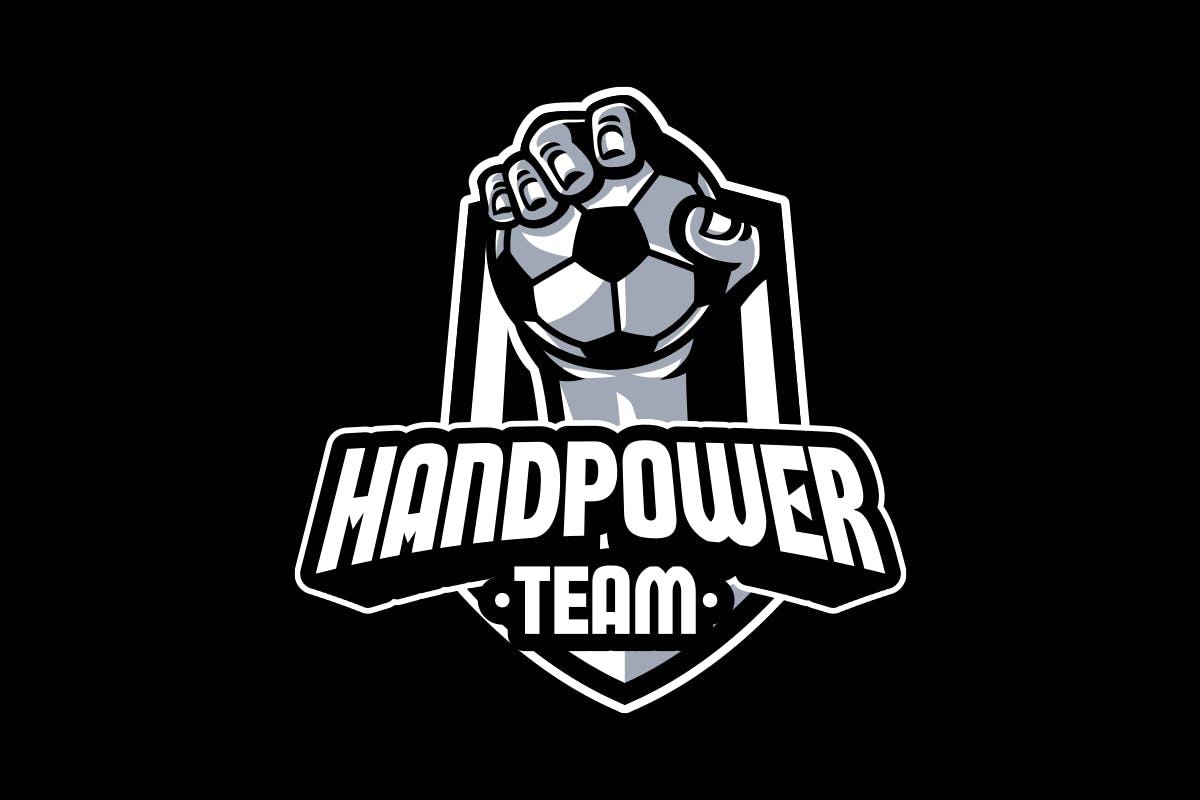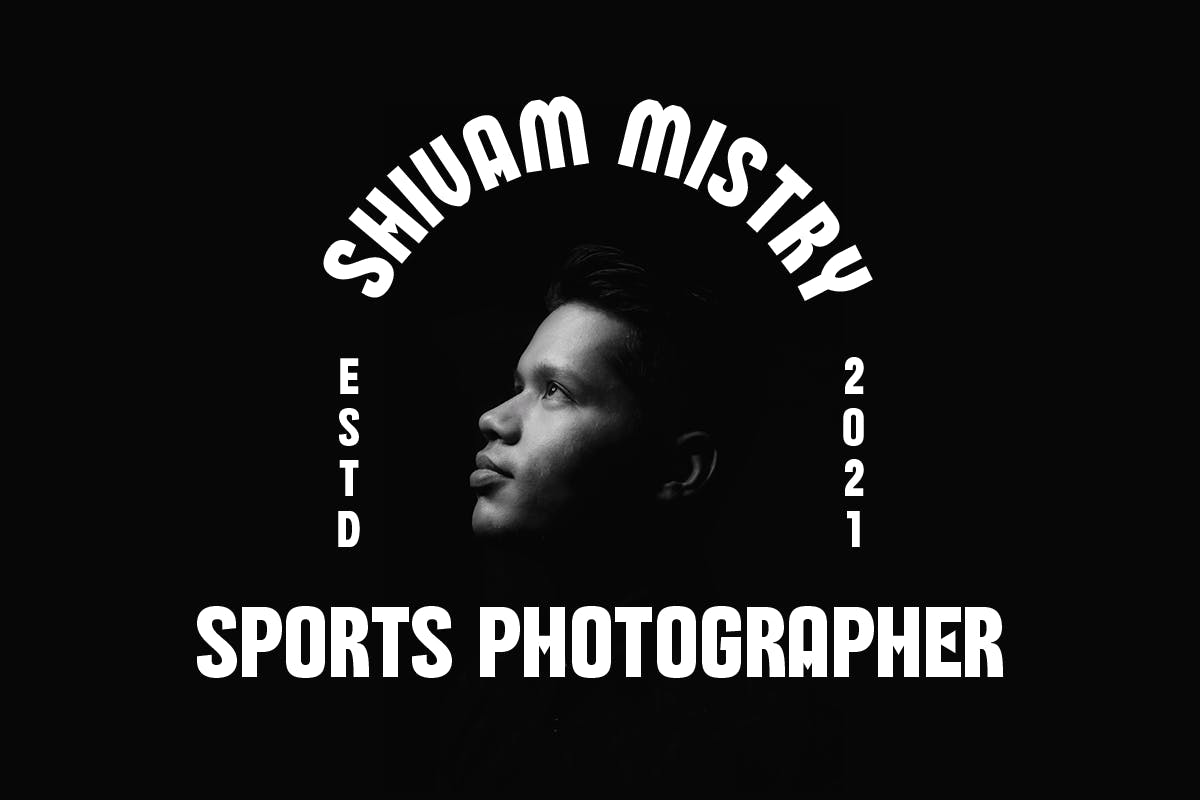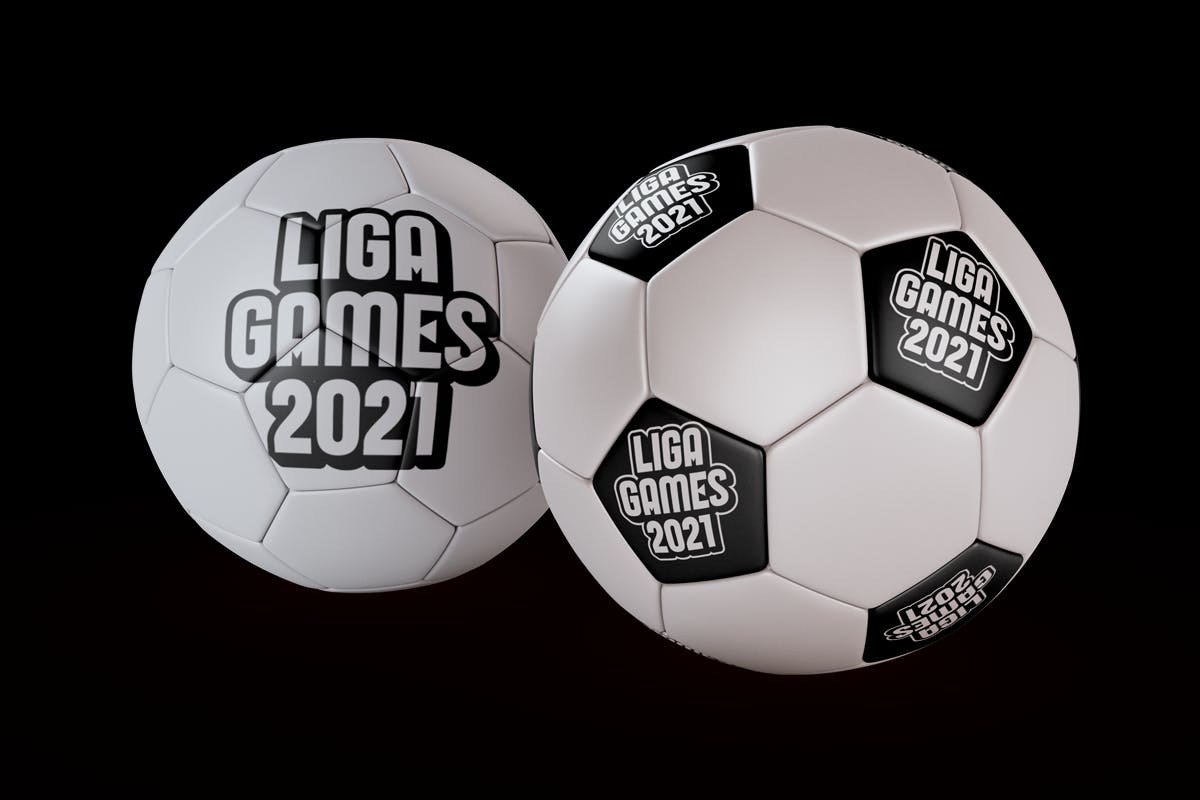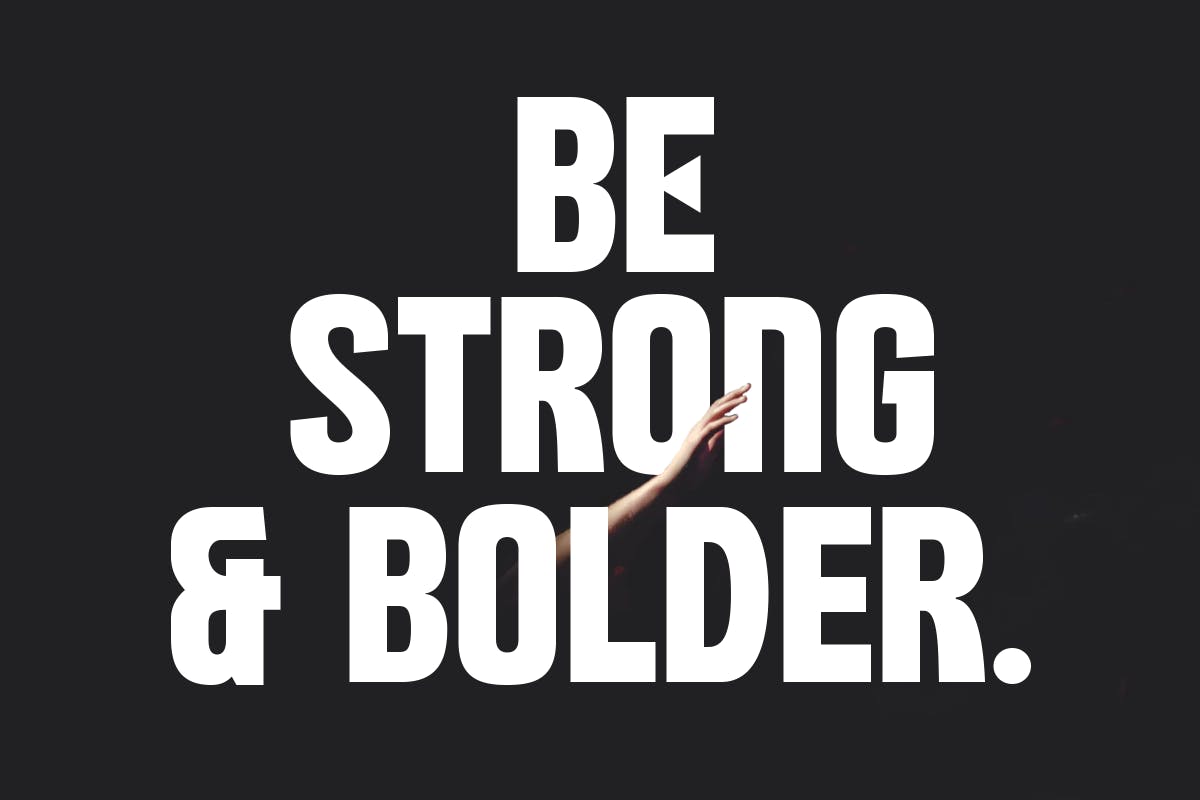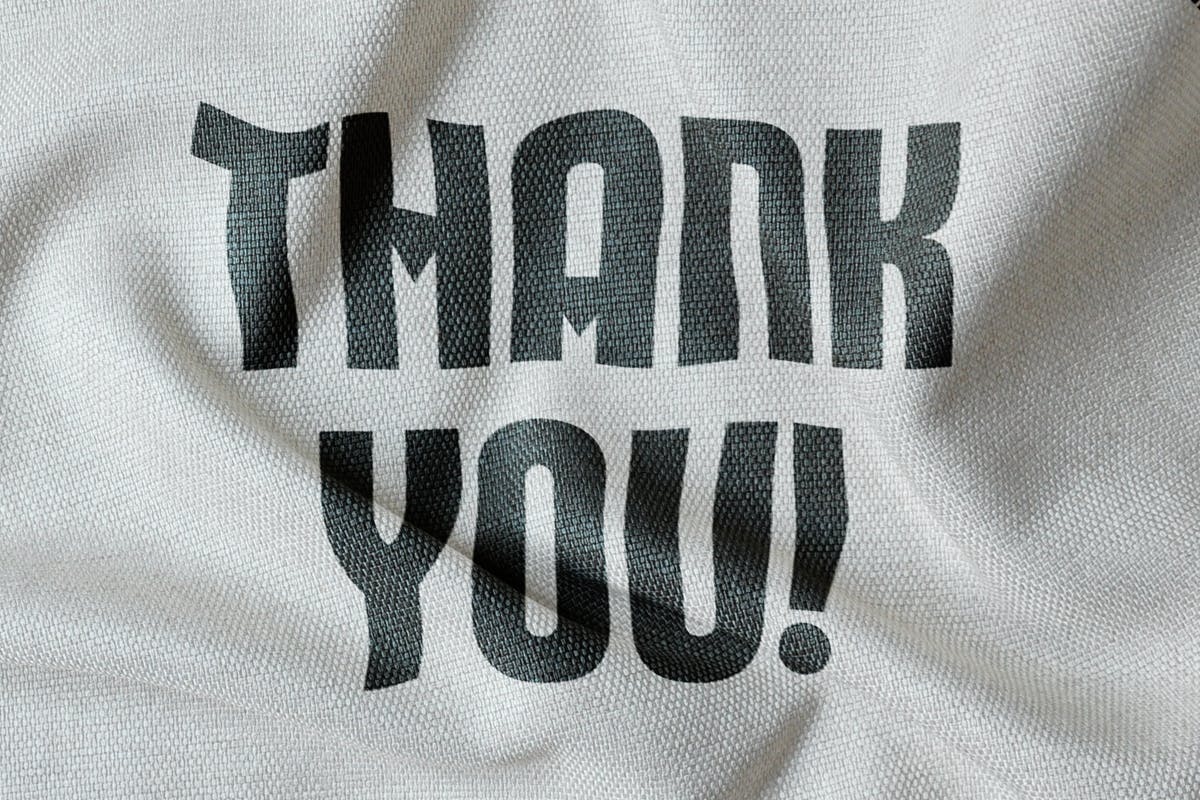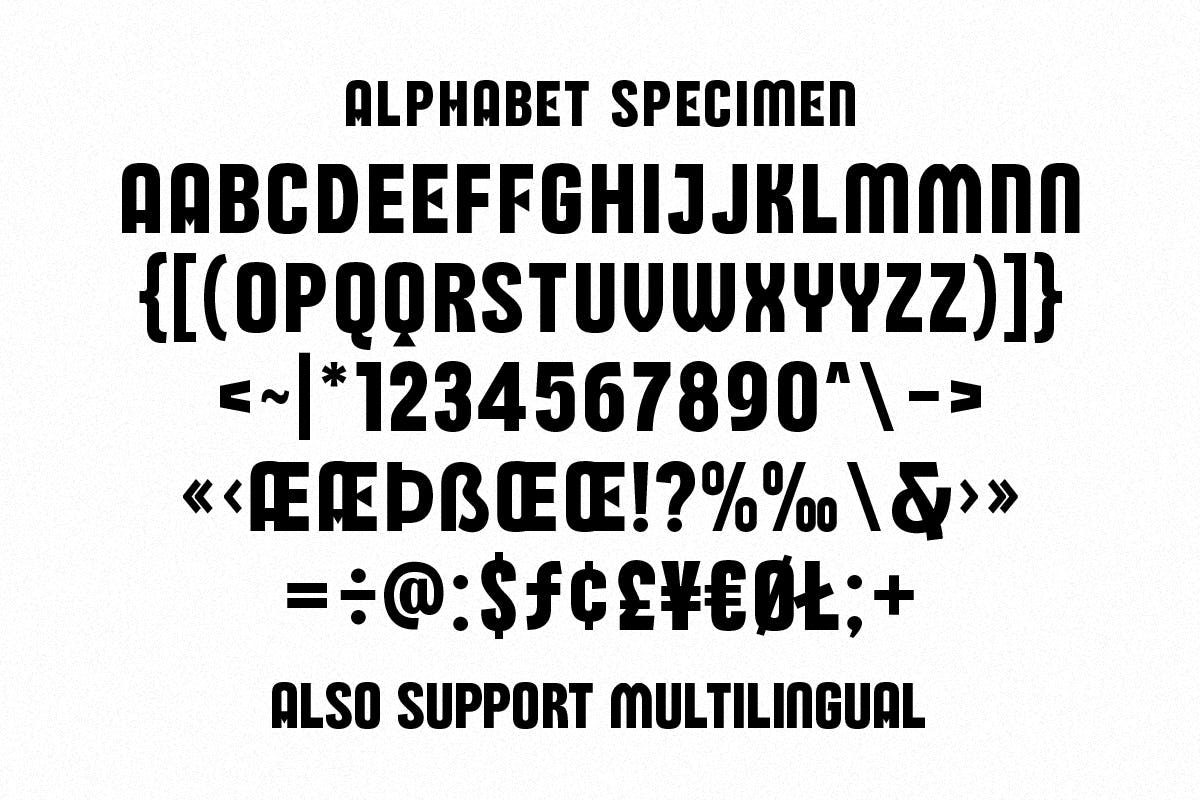
دانلود فونت لوگوی ورزشی Behover
Behover Sports Logo Font
با دانلود فونت Behover، طراحی‌های خود را جذاب‌تر کنید.
فونت Behover یک فونت بولد با سبک سنس است که با ترکیب حروف کوچک و بزرگ به شما کمک می‌کند طراحی‌های خود را آسان‌تر و با شخصیت قوی‌تری ارائه دهید. این فونت مناسب برای لوگوتایپ، لوگوی ورزشی و هر نوع طراحی دیگری که نیاز به نمایش و سرخط دارد، می‌باشد. با طراحی شاداب و جذاب خود، پروژه‌های خود را به سطح جدیدی ببرید!
• سبک بولد و جذاب
• ترکیب حروف کوچک و بزرگ
• مناسب برای طراحی لوگوها و سرعنوان‌ها